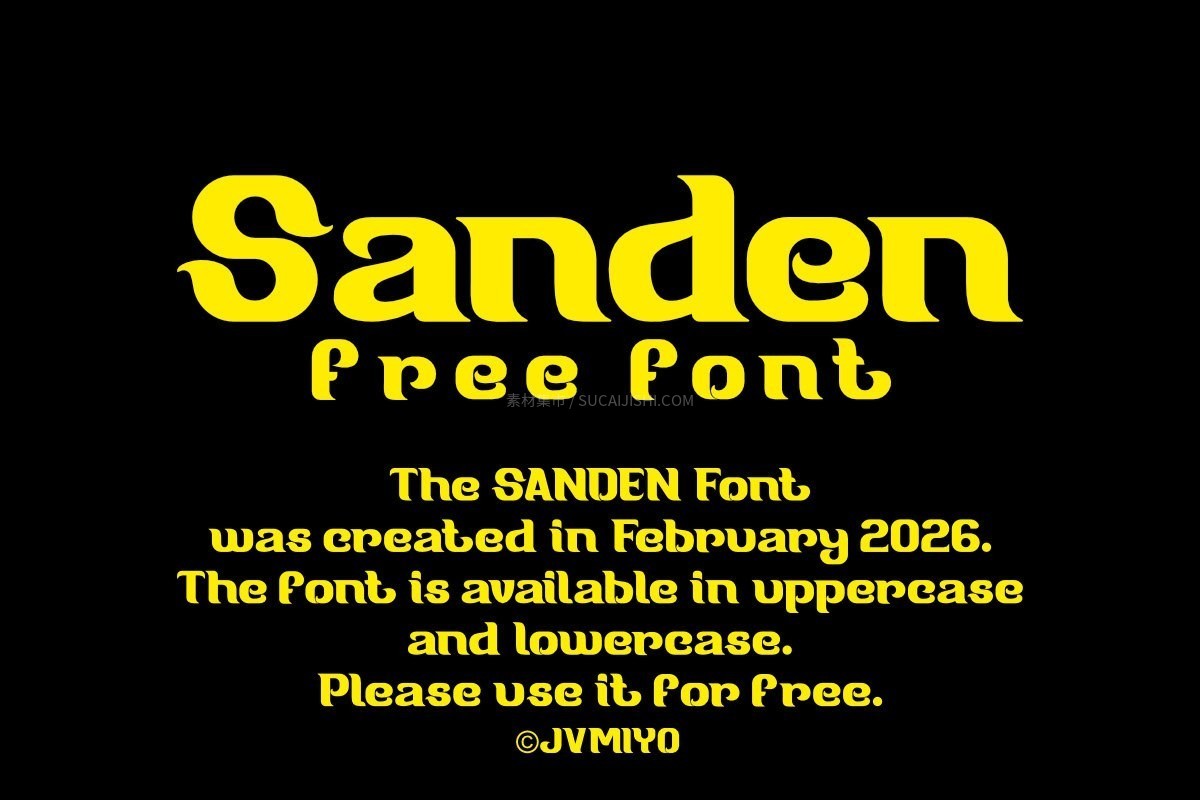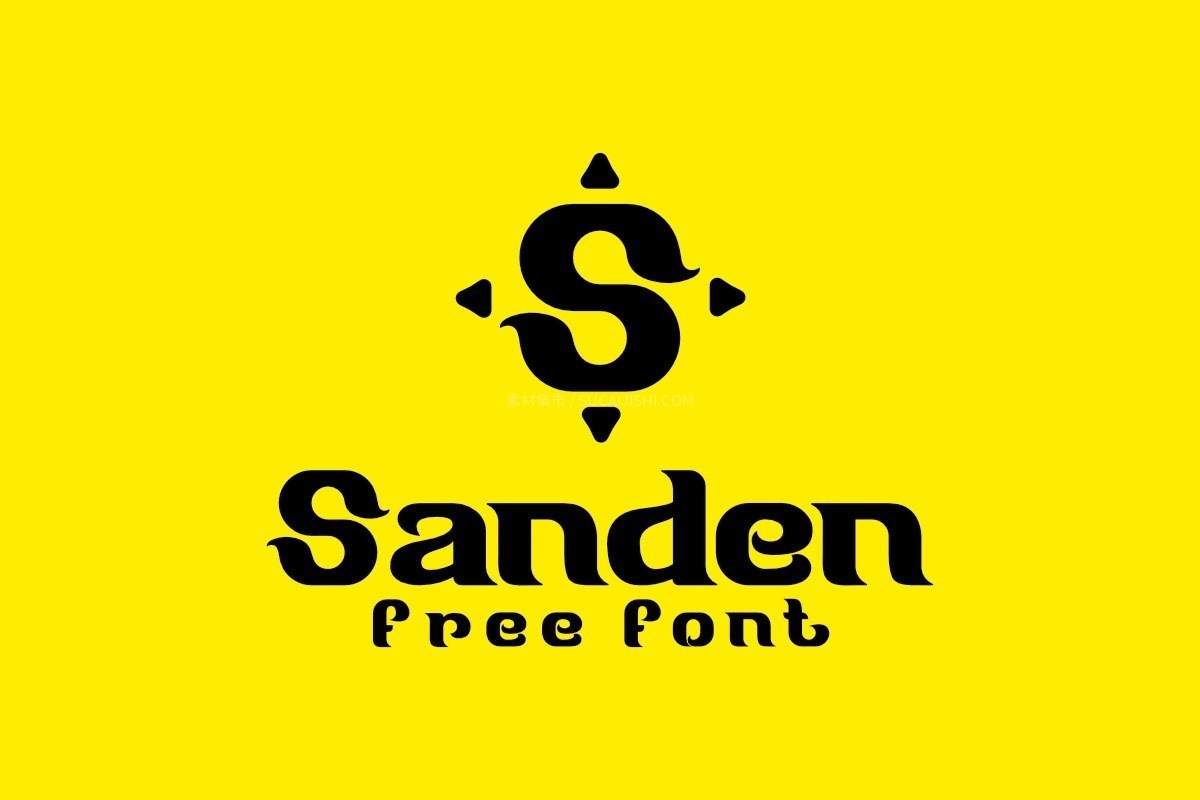
SANDEN现代时尚展示英文字体,免费可商用
这是一款由设计师 JVMIYO 倾力打造的 SANDEN 字体,融合了极简主义的洗练与灵动多变的字形。其外观简洁有力,既保留了现代时尚的工业美感,又通过活泼的曲线注入了异想天开的趣味性。这套字体采用常规(Regular)样式,包含全套标准字符,是一款极具通用性的免费展示字体。本字体已获授权,可广泛应用于个人及商业项目,是提升品牌视觉张力的理想之选。
这款字体的中宫放得好开,拿来做移动端UI正文阅读体验肯定很舒服。